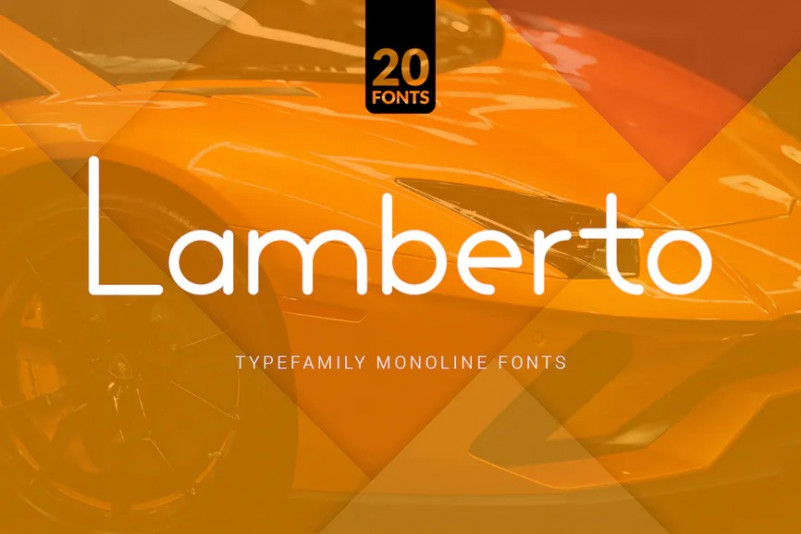
Lamberto Font
Présentation : Lamberto ! Une police monoléine avec un style et un poids de ligne unique . Avec 20 Police étonnantes, Lamberto est parfait pour l’artisanat, la photographie, le filigrane, les messages sur les médias sociaux, les publicités, les Logos et l’image de marque, les invitations, les conceptions de produits, l’étiquette, la papeterie, l’emballage de produits, les événements spéciaux, etc.